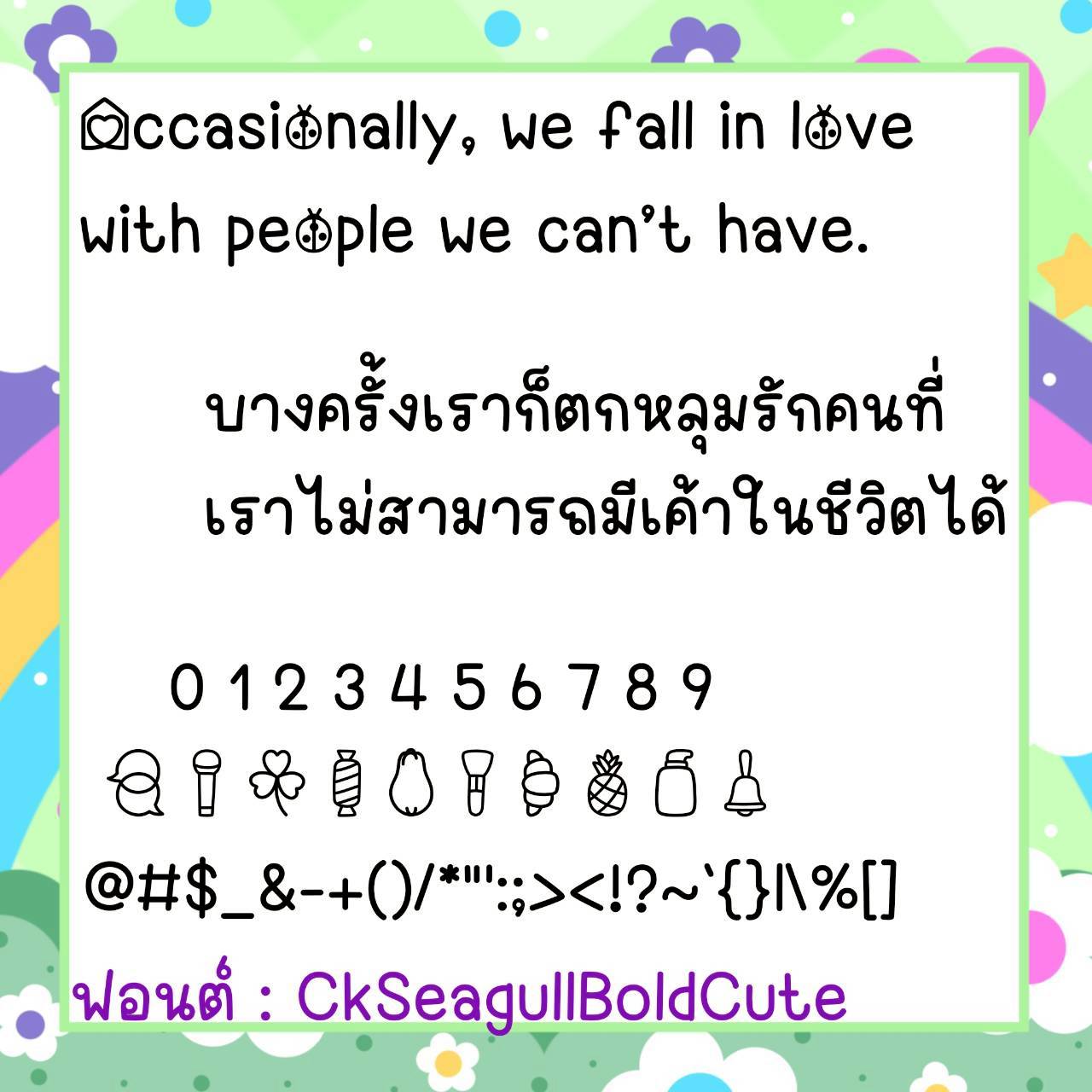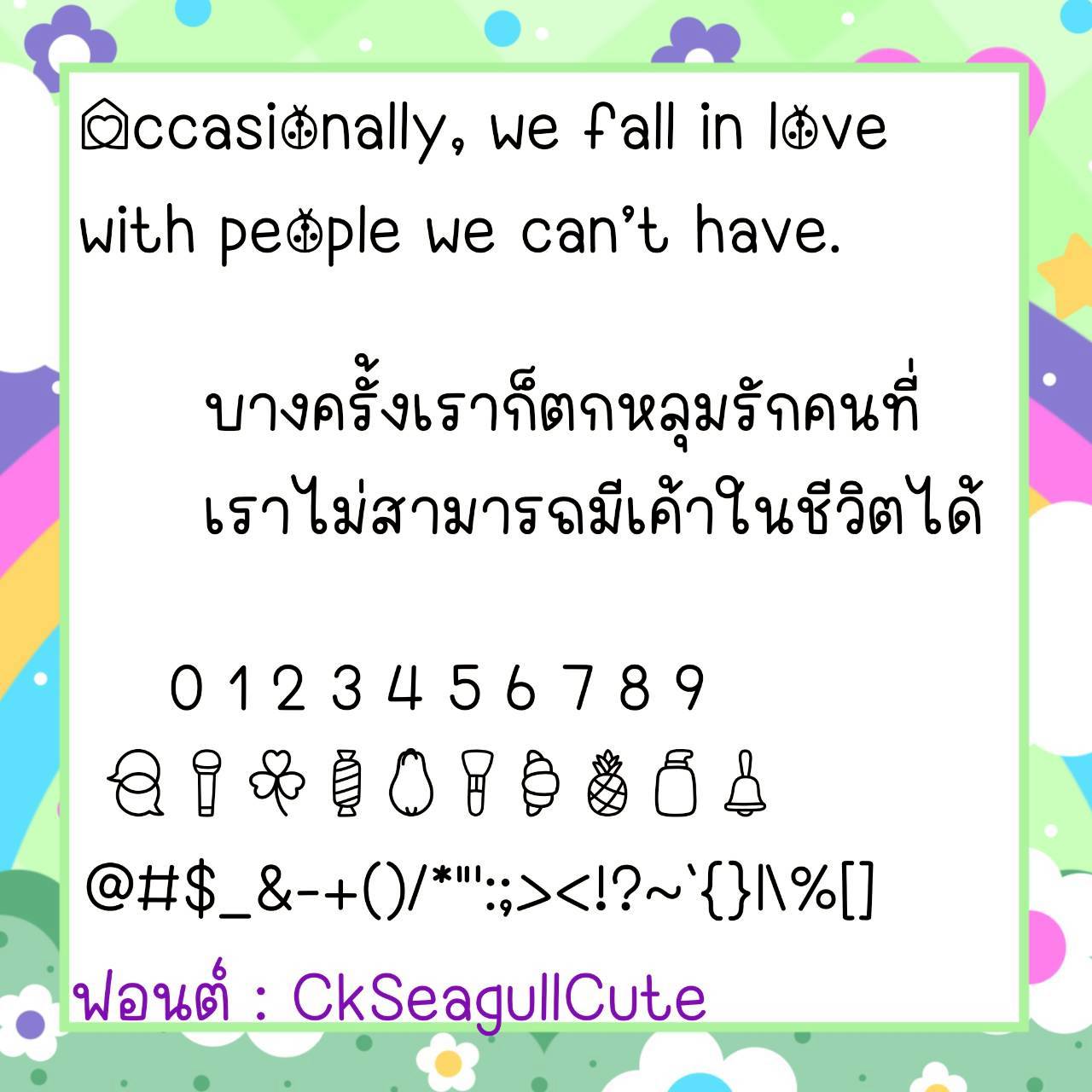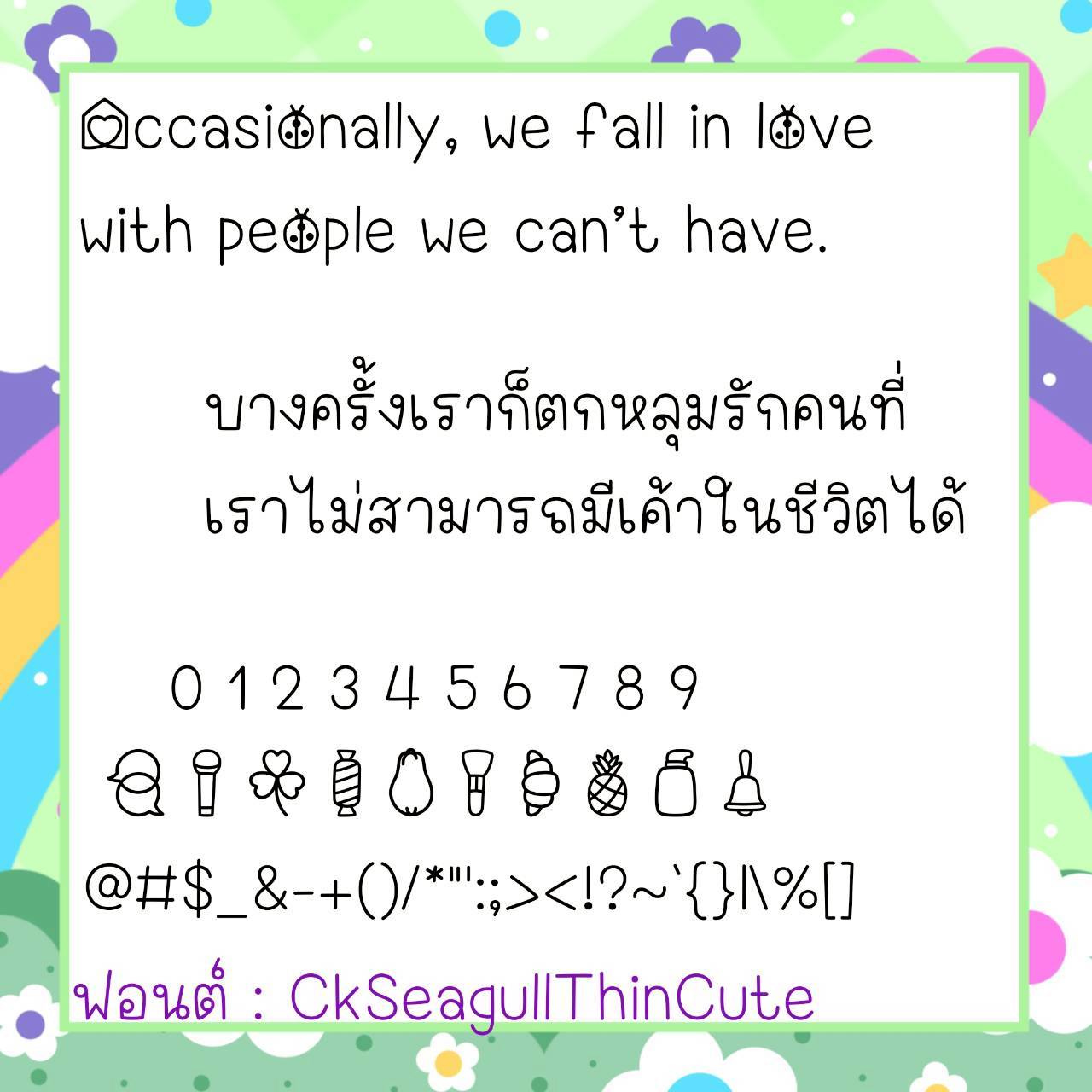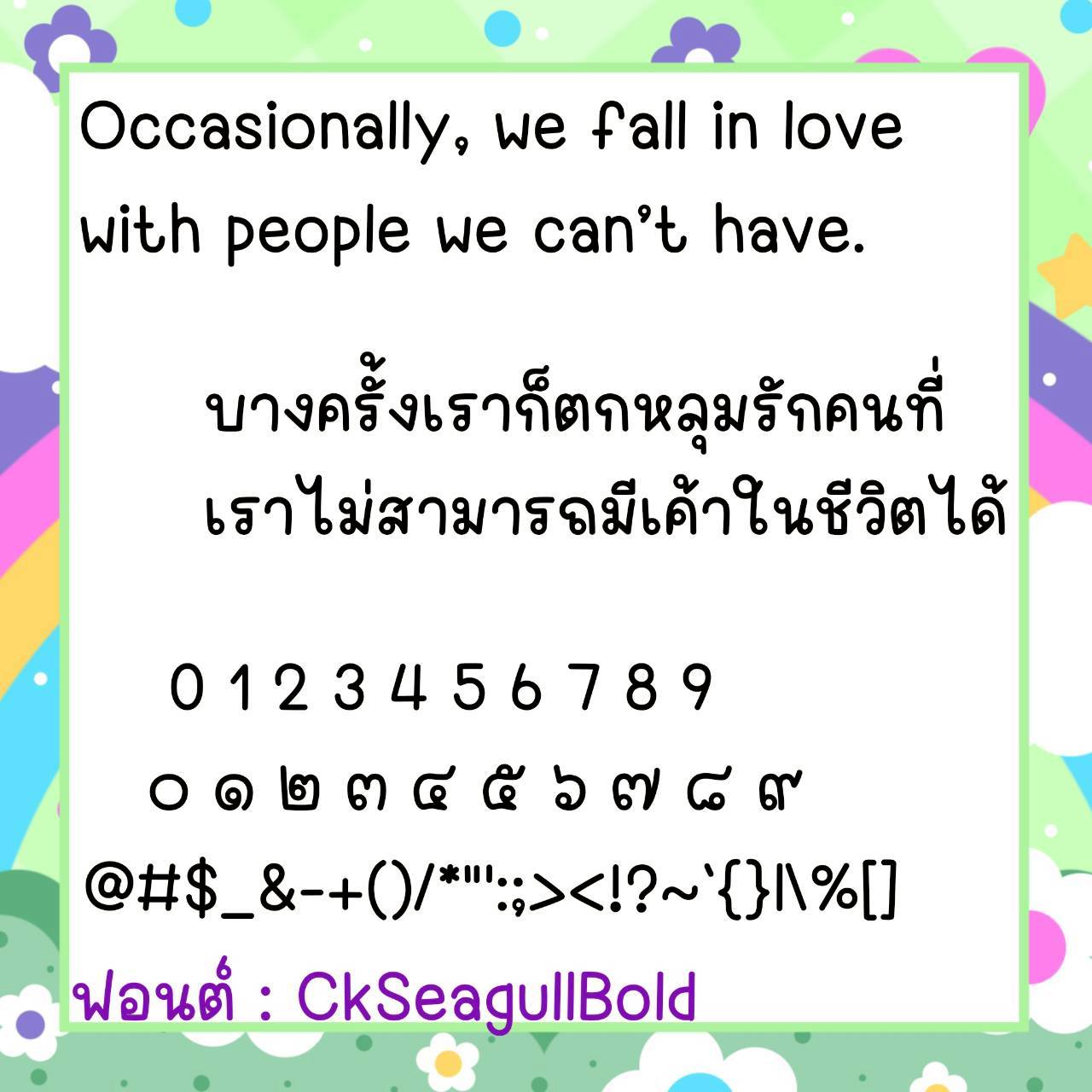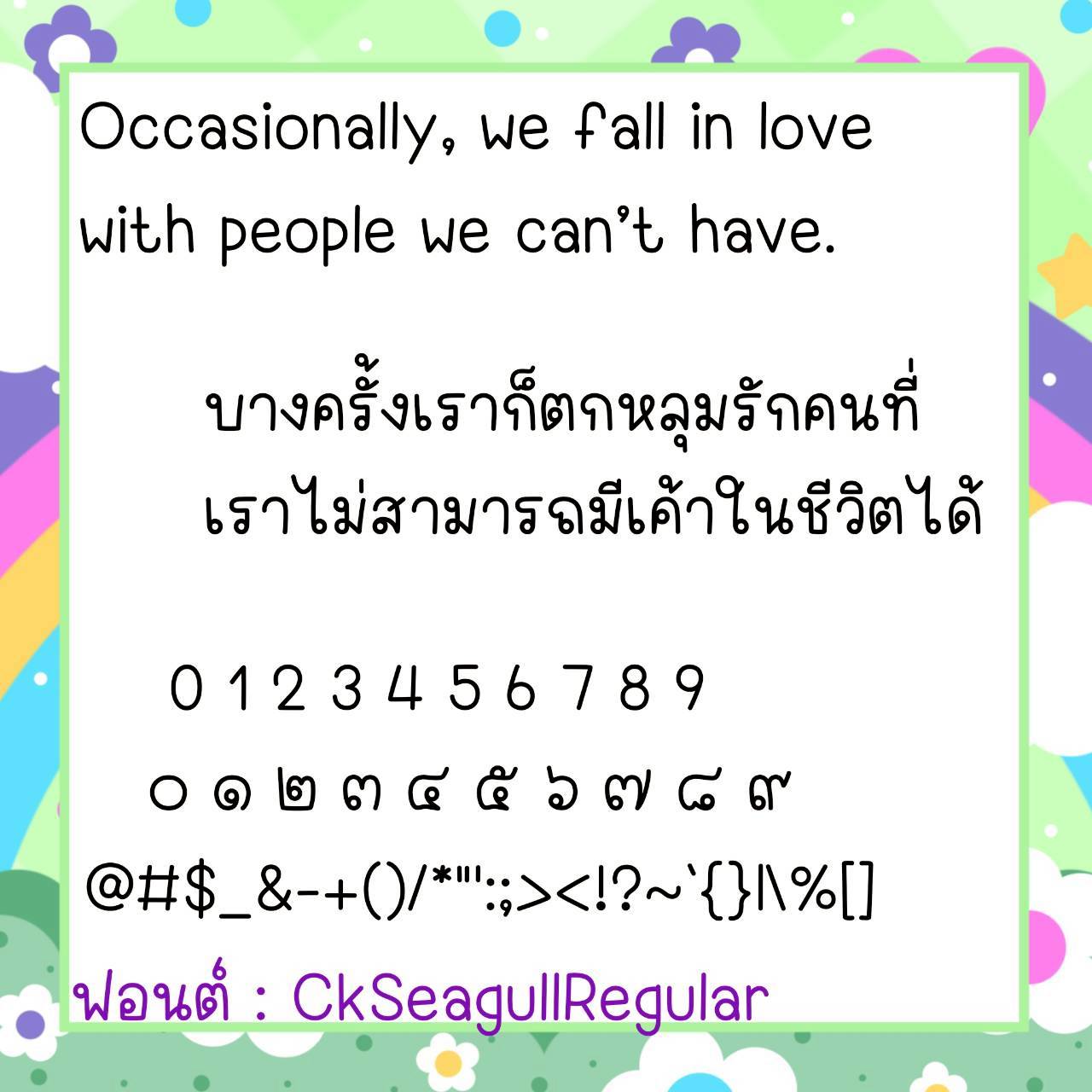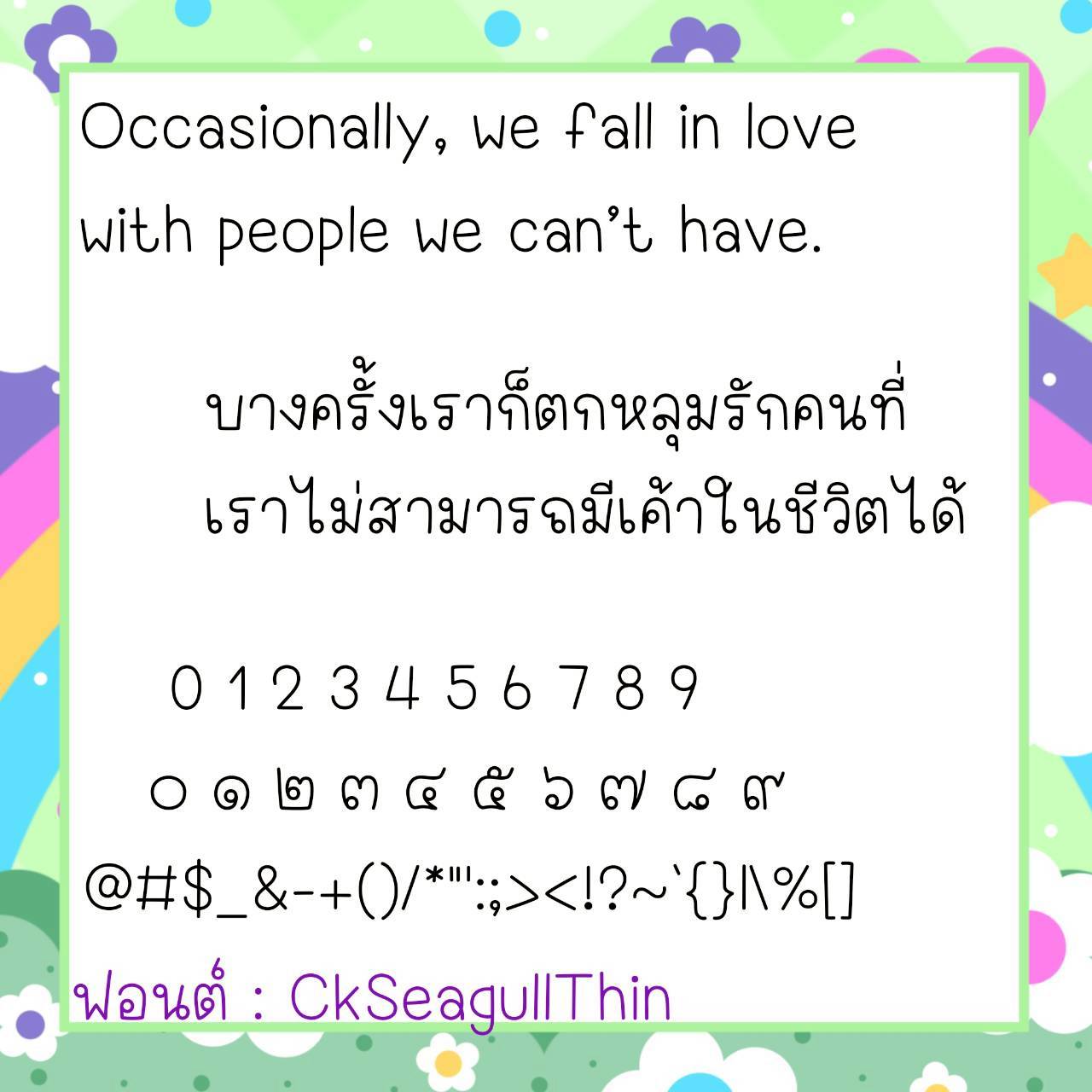
Font CkSeagull
🔸 ฟอนต์ลายมือแนววัยรุ่น มีความยึกยัก น่ารักมีสไตล์ดูมีลูกเล่น ดูไม่น่าเบื่อ และยังมีไฟล์อิโมจิน่ารักๆที่ใช้แทนเลขไทยให้ด้วยค่ะ 🥰💙
🔹 This trendy, handwritten font has a cute, playful, and stylish vibe that’s anything but boring. It also includes cute emoji files that can be used to replace Thai numerals. 🥰💙
🔸ฟอนต์ลายมือแนววัยรุ่น มีความยึกยัก น่ารักมีสไตล์ดูมีลูกเล่น ดูไม่น่าเบื่อ และยังมีไฟล์อิโมจิน่ารักๆที่ใช้แทนเลขไทยให้ด้วยค่ะฟอนต์ปรับสระเรียบร้อยไม่ลอย ไม่เหลี่ยม ใช้งานได้กับทุกโปรแกรม ได้ทั้ง ios(รองรับกับแอพต่างๆที่รองรับฟอนต์ในios เช่น Goodnote, Procreate)/android/คอมฯ/Ps/Word,Excel ได้หมดจ้าาาาา❤️❤️❤️